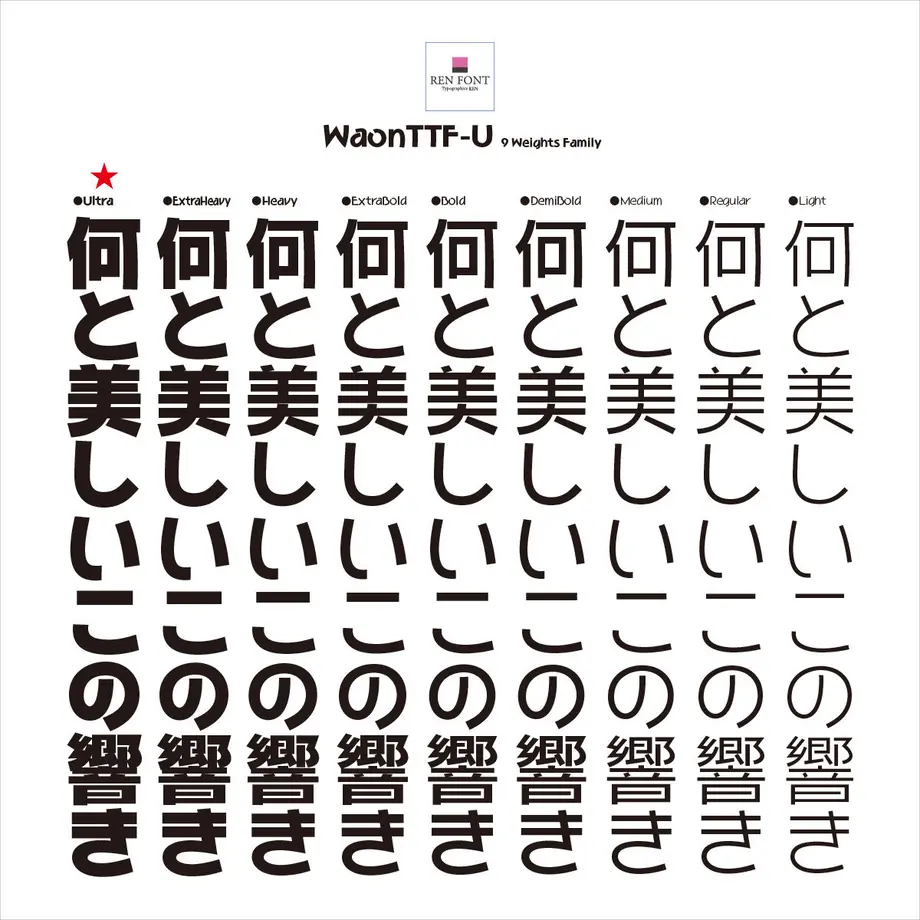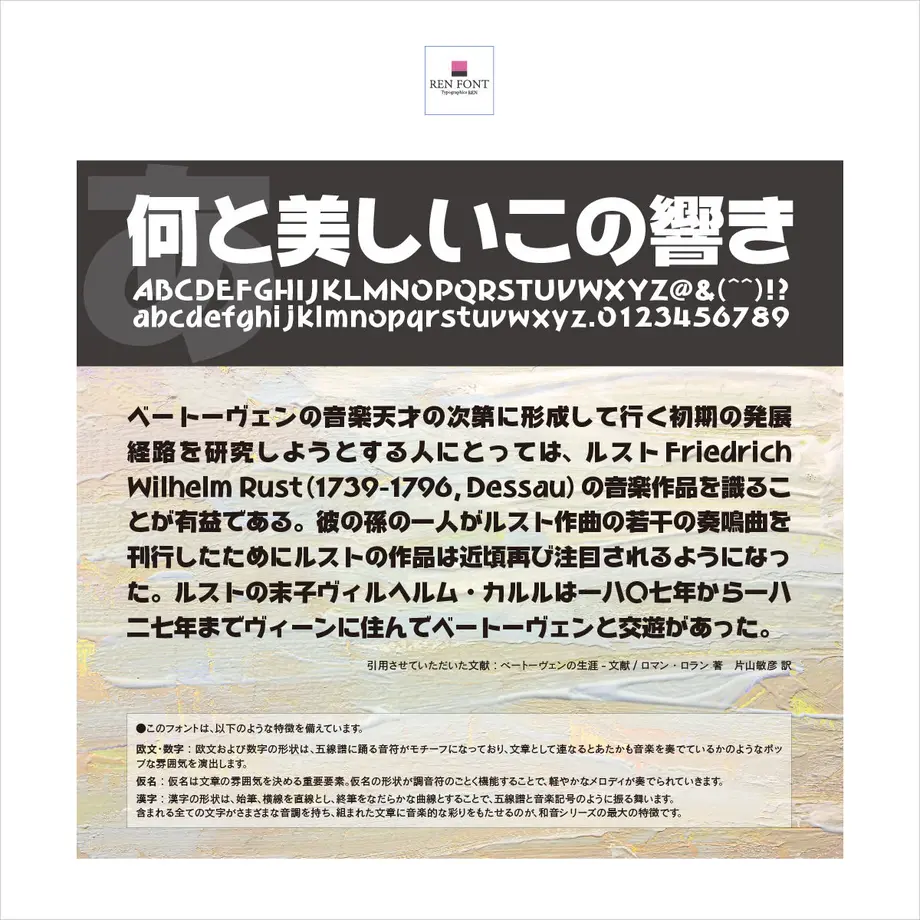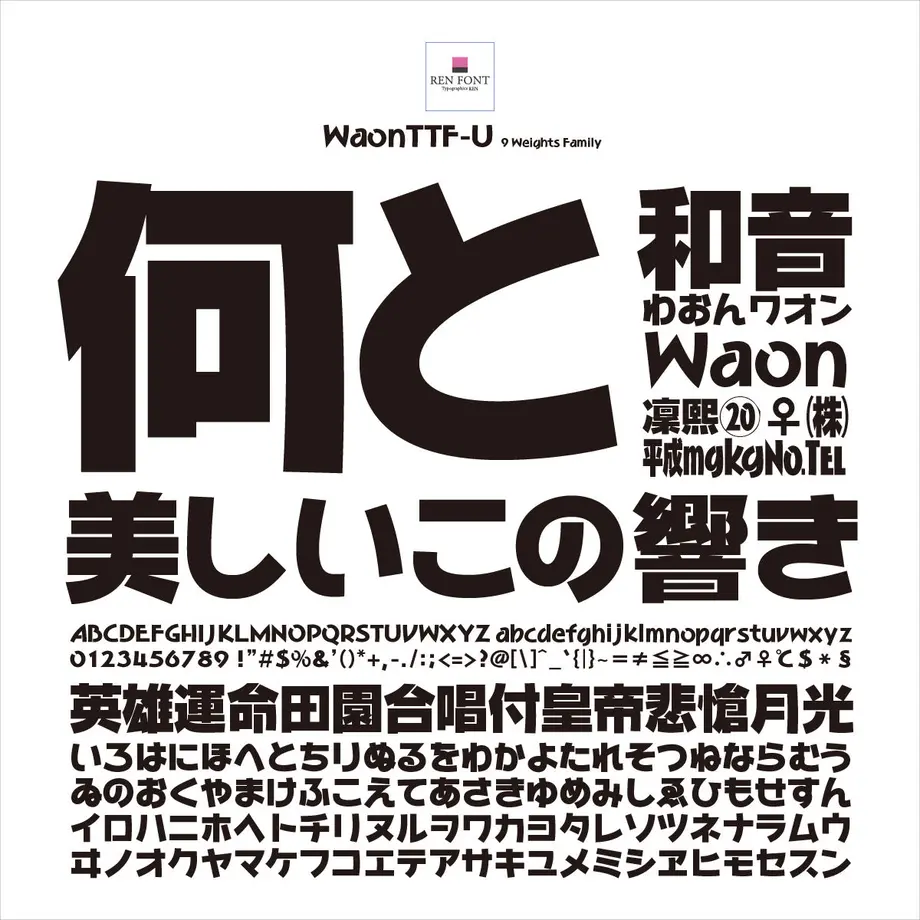
オールマイティな使用感のフォント
和音TTF 9ウェイトファミリー / TrueType
和音ファミリーの各書体は、2005年度特定非営利活動法人日本タイポグラフィ協会により開催された「日本タイポグラフィ年鑑2005」コンテストの書体部門入選作「和音」を源流とし、制作されています。
漢字、平仮名、片仮名、欧文、記号類、用途字種、数字の各字種のそれぞれに音楽的特徴をもたせ設計、それぞれがもつ特徴が見事に調和する、制作期間2年以上の全てを注ぎ込んだ当社タイプデザイナー金井和夫、渾身の労作です。
この書体は、最細ウェイト「L(ライト)」から最太ウェイト「U(ウルトラ)」に至るまで、合計9ウェイトを数学的アプローチで中間生成するという試みのもと、制作されております。まさに「和音=ハーモニー」の名にふさわしいできとなっておりますので、是非さまざまなシーンでご利用いただければ幸いです。
●EH[エクストラヘビー]
●漢字
ほとんどの文字のどこか1か所が切れて離れたデザインになっており、スタッカートのようなアクセント豊かな効果が生まれます。
また、終筆の跳ねをなくして緩やかな曲線しました。これは、指揮者が振り下ろし振り上げるタクトの軌跡を表現しています。 すべての文字に伸びやかさとおおらかさを与え、組まれた文章に音楽的な彩りや愉しさをもたらします。
文章の約70パーセントを占めるといわれる仮名。作品の雰囲気を決める重要要素といって過言ではありません。
音楽に欠かせないリズムを表現するために、終筆をあえて中途半端な長さに終わらせて不安定にし、和音と相反する「不協和音」を表現し、動きを与えました。
まるで音符のように機能し、オペレッタのような、可愛らしく軽やかなメロディが奏でられていきます。
「和音」の基本コンセプトである「文字で音楽を表現する」を、最も端的に文字通りに「表現」しているのがこの従属欧文です。形状は、五線譜に踊る音符がモチーフになっています。とくに「d」「p」は四分音符そのものです。
サンセリフ書体は、一般的にエクスハイトが高めにデザインされています。それにより一文字ひともじが大きめになり、セリフ書体と比べて、現代的な雰囲気が強くなります。「和音」は、さらにエクスハイトを高めにし、大文字と小文字の差があまりありません。また、小文字のふところをより広めにデザインすることで、楽しさ愛らしさを表現しました。